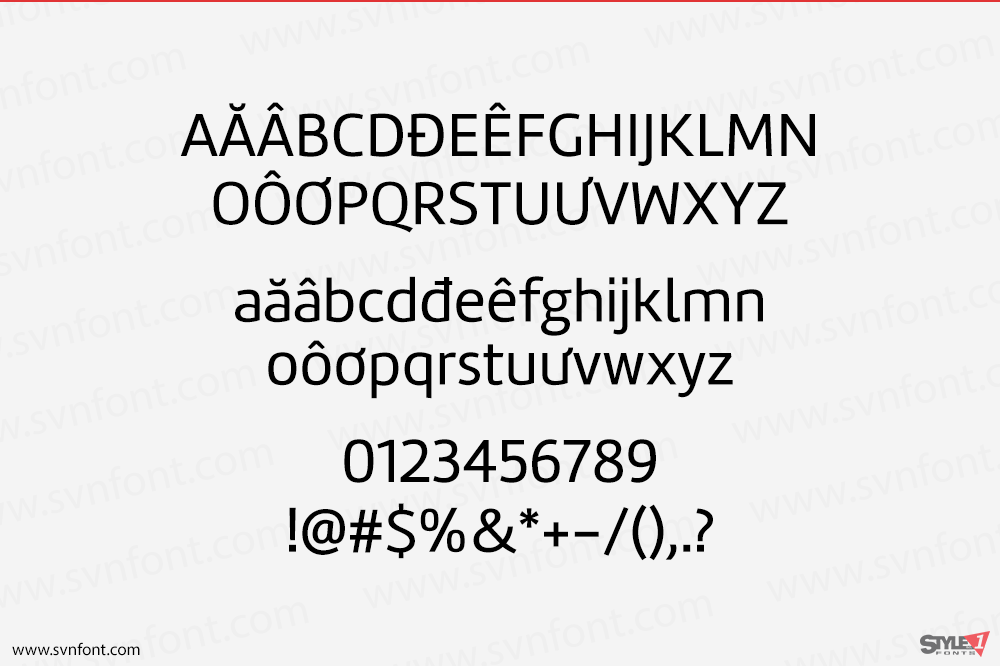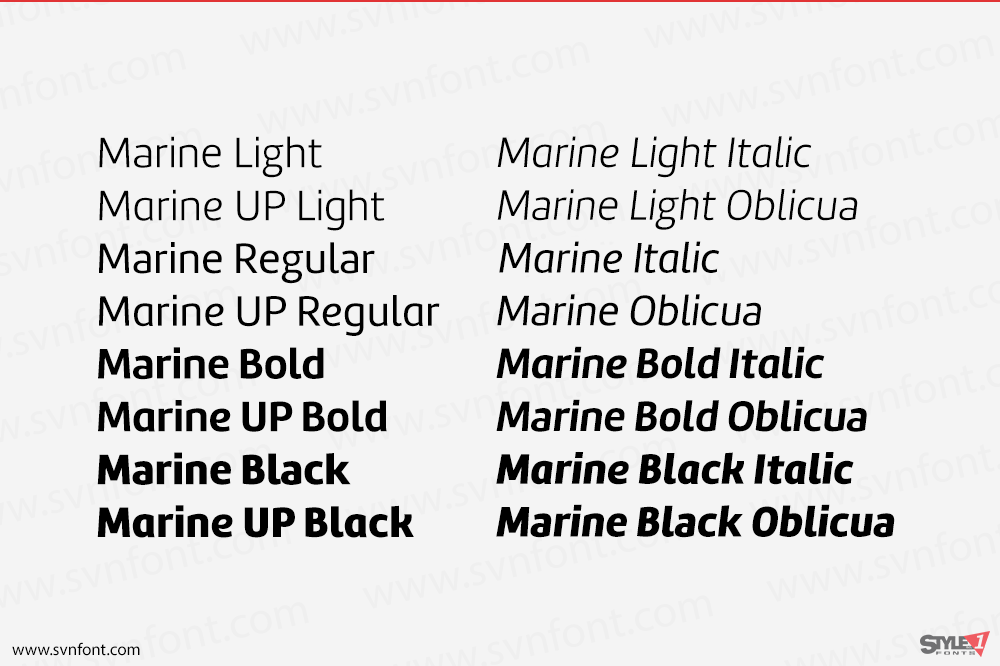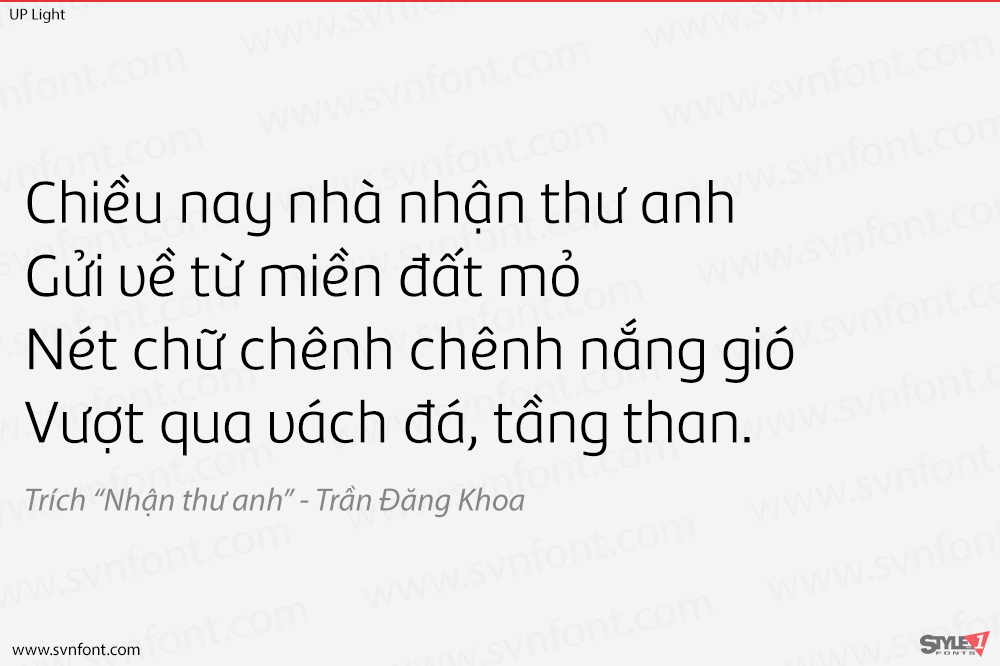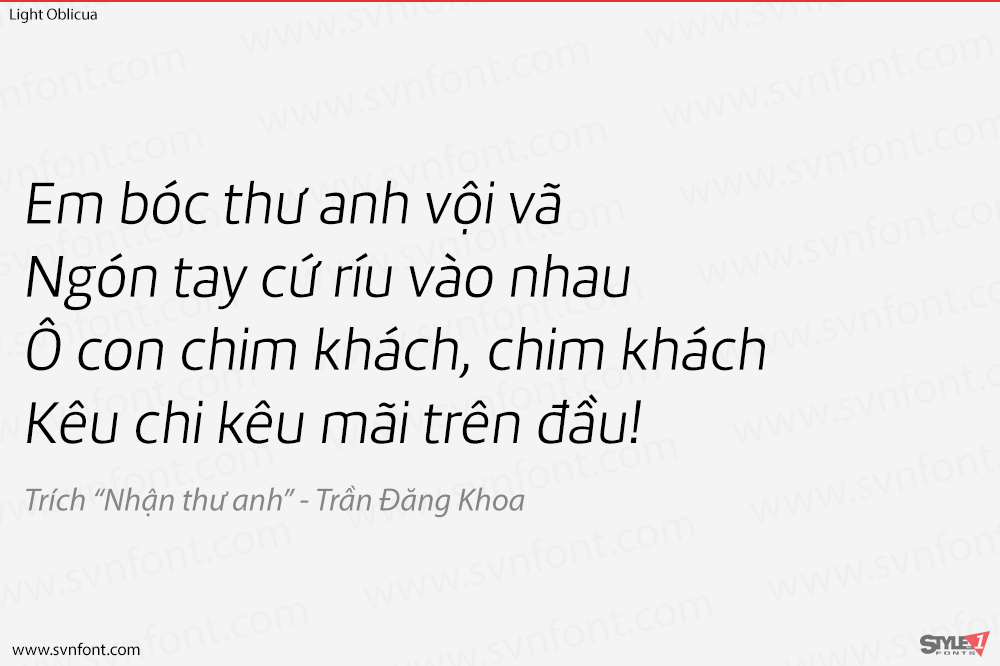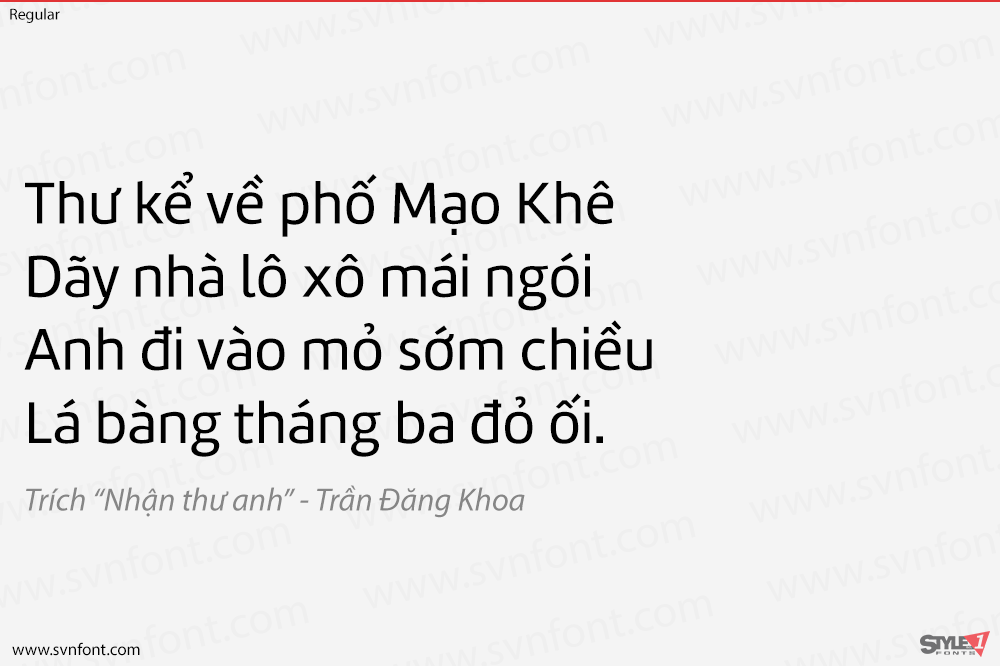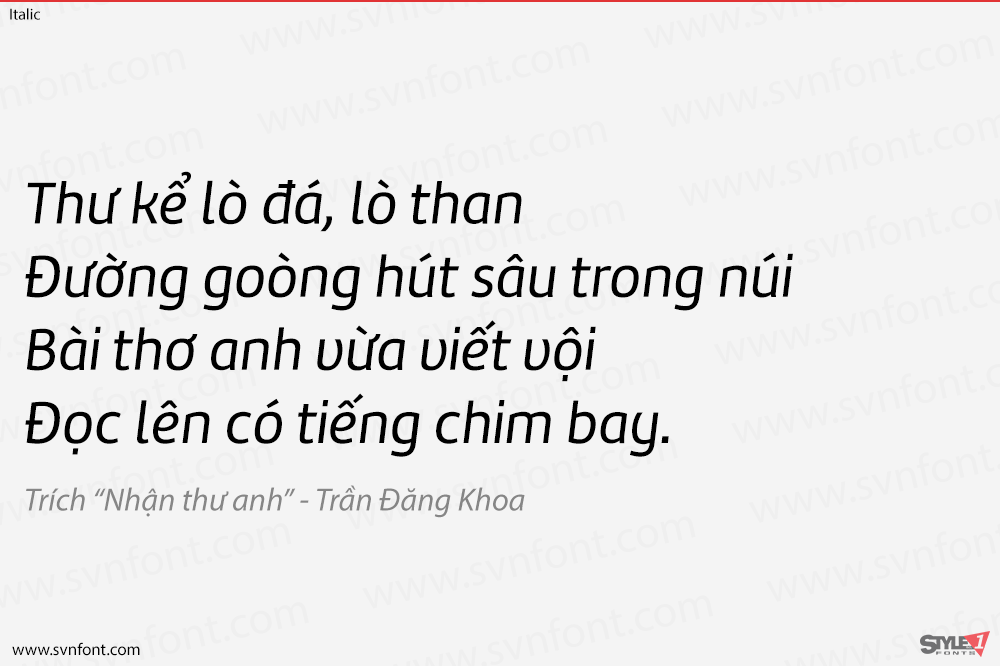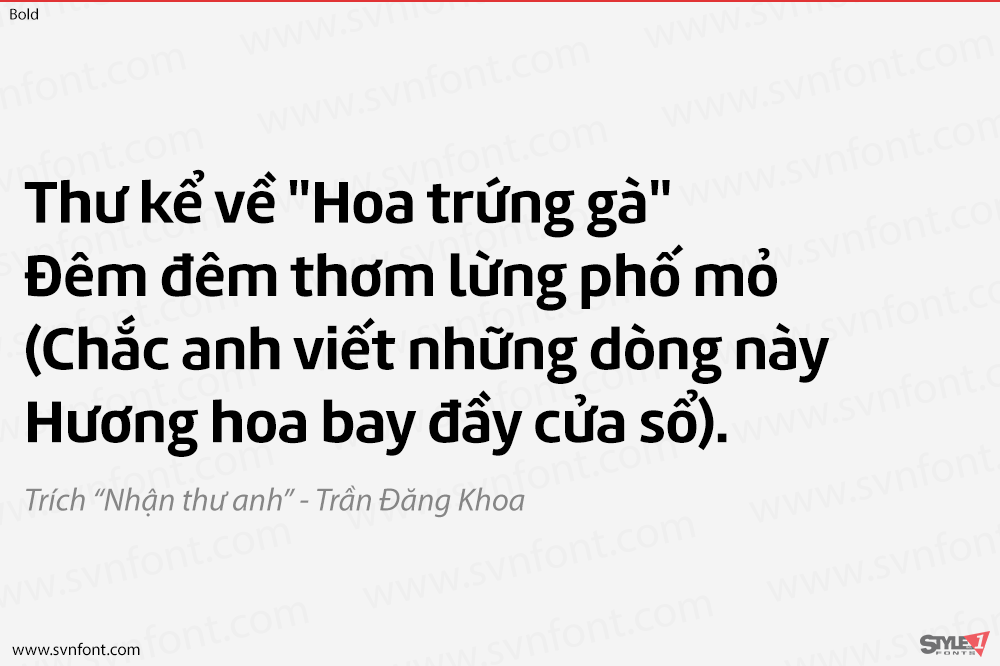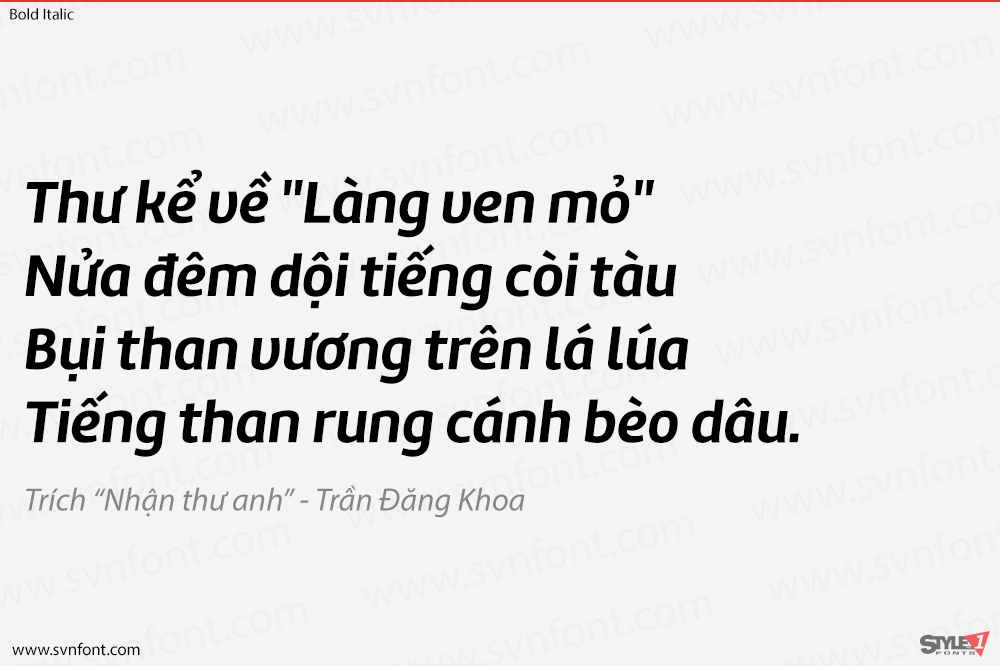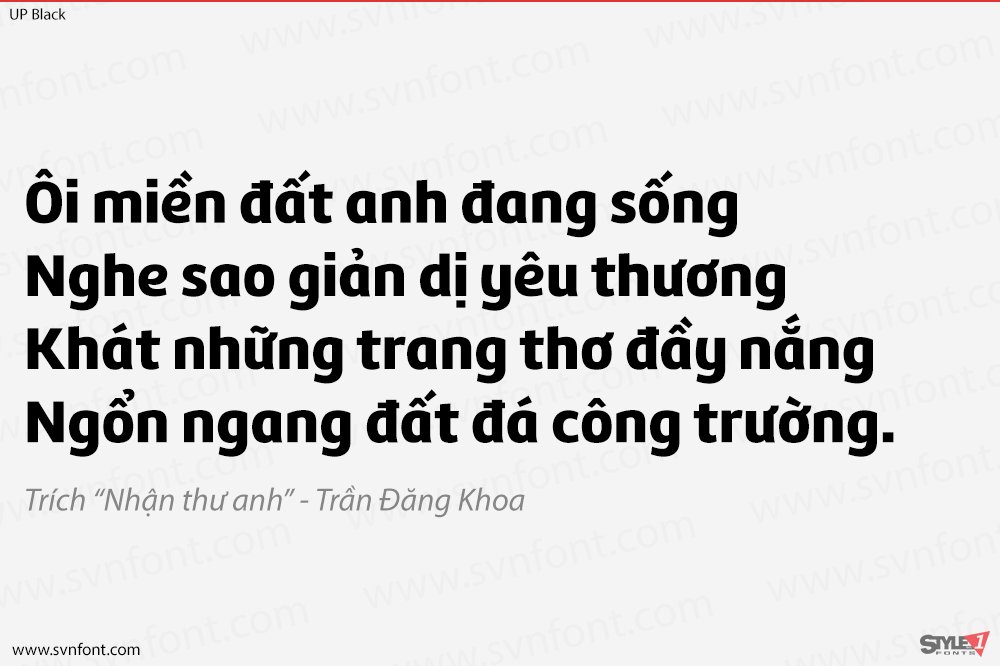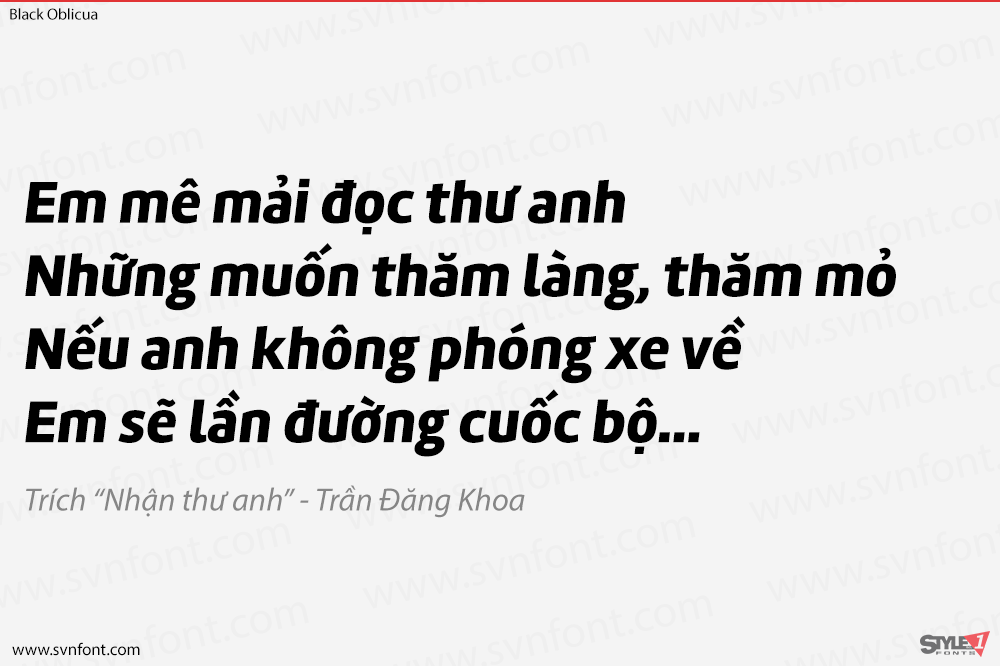
Marine là một font sans serif hình học nhưng mang sự mềm mại của những nét viết tay. Độ tương phản nhẹ và nhiều kiểu dáng khác nhau cho phép Mariné hoạt động tốt như cả một font chữ văn bản và font hiển thị. Nó cũng bao gồm một phiên bản Up và các tính năng thư pháp, thêm một chút sự không trang trọng. Mariné có sẵn trong một họ font mở rộng và là họ hàng gần của Amelia. Tất cả các khác biệt giữa Mariné và Amelia xuất hiện ở các phiên bản nghiêng và Up.
Nhà thiết kế: Martin Sommaruga
Nhà phát hành: TipoType